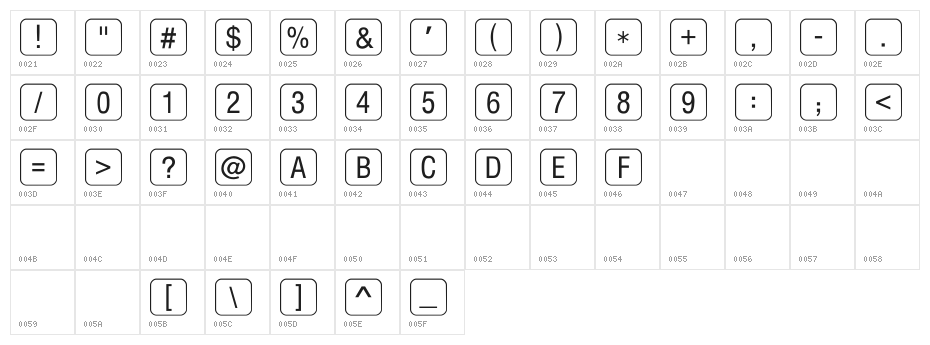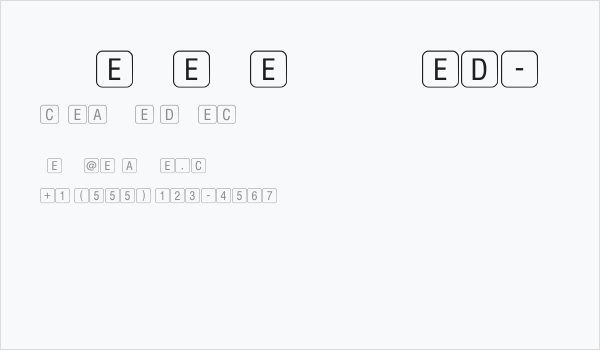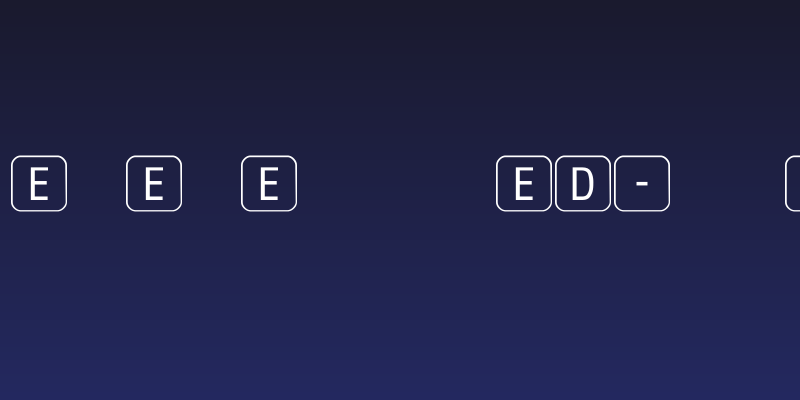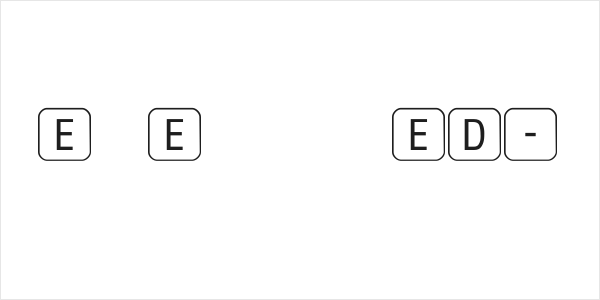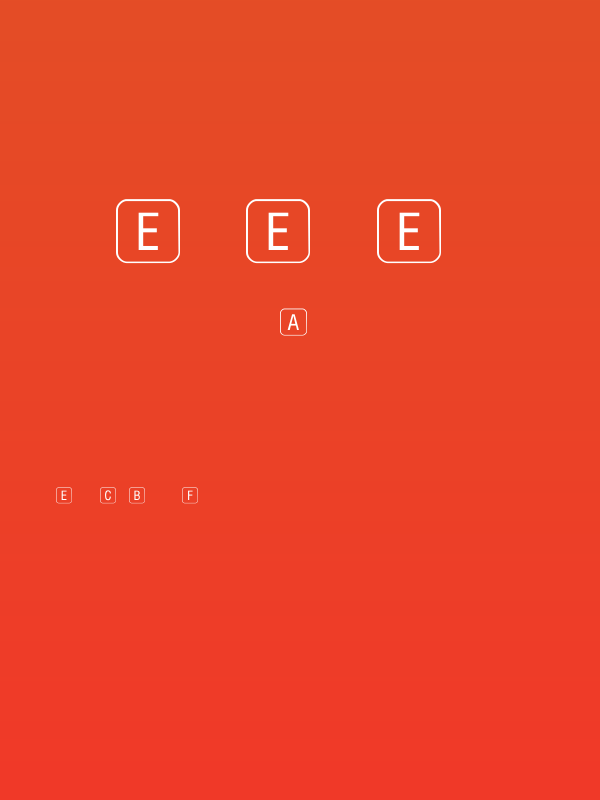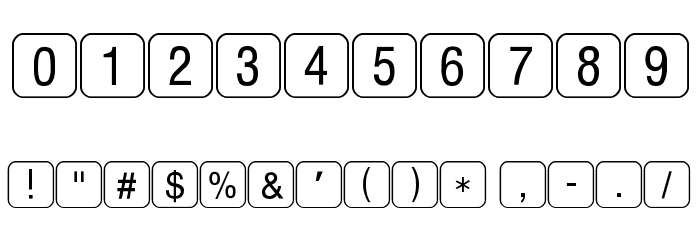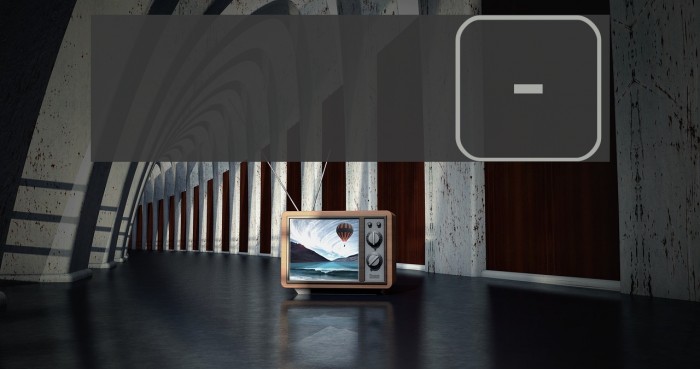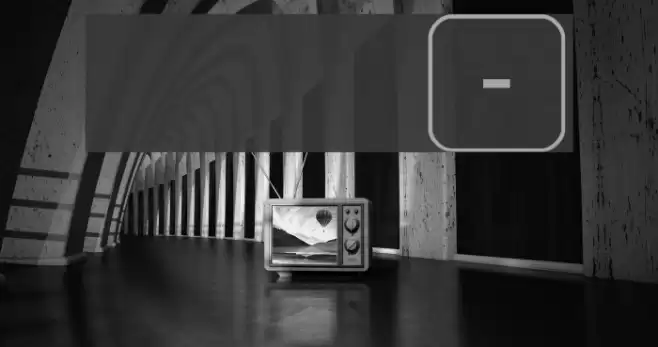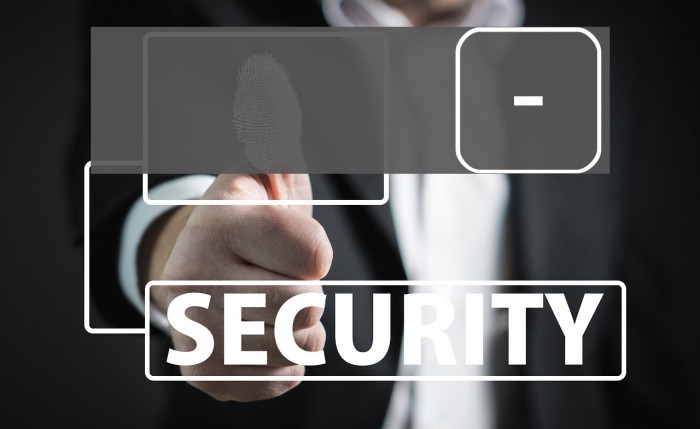
RRKeyLettersLimited-Normal Font
✎ Technical
| Catégories | Technical |
| Cas d'utilisation | Headlines, Logos, Signage |
| Projets proposés | Ideal for retro-themed designs, branding, signage, and any project requiring a mechanical or typewriter-inspired aesthetic. |